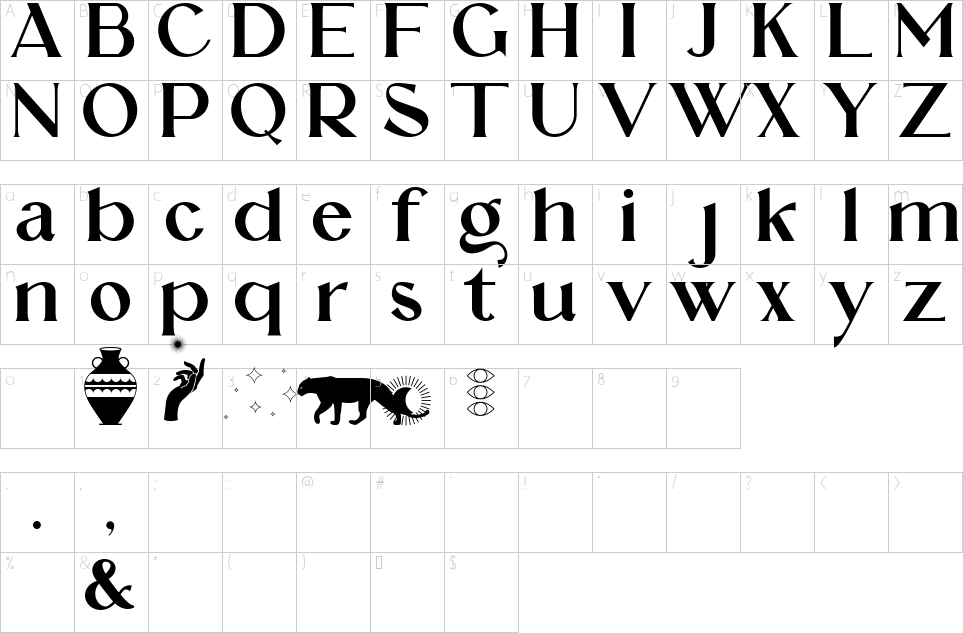
A fonte Aqrada é uma escolha ideal para quem busca um estilo moderno e elegante. Desenvolvida pelo designer indonesio Putu Dody Permana, esta fonte é perfeita para adicionar um toque de sofisticação a seus projetos digitais. Com um design minimalista e limpo, Aqrada destaca-se em qualquer fonte. Desde o título de um site até a tipografia de uma carta de negócios, esta fonte oferece uma variação de pesos e estilos para satisfazer todas as necessidades de design. Download Aqrada para Windows e Mac, é uma fonte gratuita que você vai querer usar em todas as suas criações. Com uma sólida base de downloads de mais de 396 vezes, você pode confiar que Aqrada está se tornando uma fonte popular e valiosa para designers de todo o mundo.